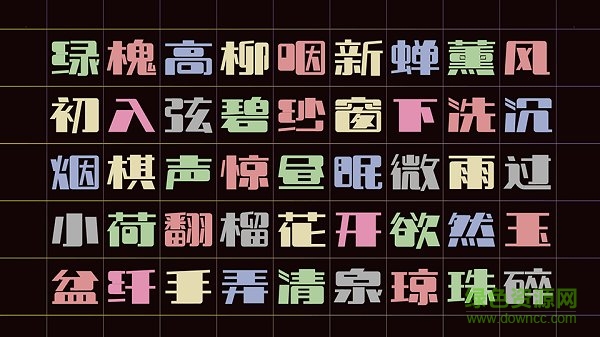
樂敦體是喜鵲造字推出的第二款字體,整體形象飽滿,筆畫粗細(xì)相間,線條端正形態(tài)迥異,如同活潑調(diào)皮的小胖孩,藝術(shù)效果比較出色,快來綠色資源網(wǎng)試試吧!
樂敦體,也是當(dāng)時在網(wǎng)上呼聲比較高的一個字體風(fēng)格。我經(jīng)常去潘家園收老美術(shù)字的舊書,所以對一些民國時期或者新中國時期典型的老美術(shù)字很感興趣,經(jīng)常試著仿寫平頭筆美術(shù)字。
于是畫了一種粗細(xì)對比強(qiáng)烈,轉(zhuǎn)角圓潤的標(biāo)題字體。由于字體如果筆畫粗的話,很容易產(chǎn)生壓迫感和嚴(yán)肅的感覺,所以我在電腦上制作這個字體的時候,在保留識別度的基礎(chǔ)上把一些書寫筆畫中的穿插交疊改成了一種俏皮戲謔化的搭建,讓每個字看起來都像是有表情的一個個胖墩墩小胖孩兒。有歡快的感覺,所以叫做樂敦體。
適用于現(xiàn)代綜藝風(fēng)格和復(fù)古美術(shù)字的標(biāo)題文字需求,
如復(fù)古海報、廣告標(biāo)題、創(chuàng)意產(chǎn)品、綜藝字幕等。